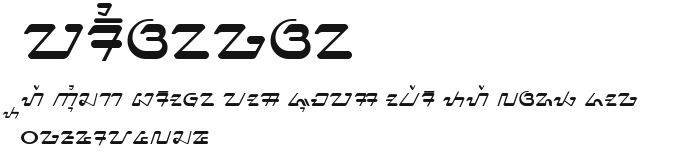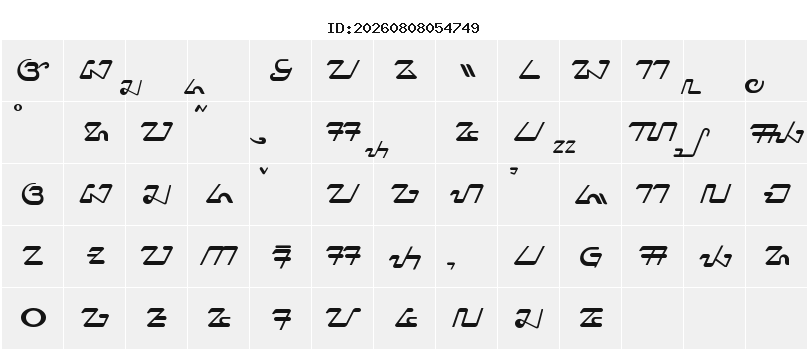
• Font Name: Priangan
• Designer: Indra Afriana
• Description: Aksara Sunda Baku nyaéta aksara Sunda kiwari nu diadaptasi ti aksara Sunda kuna. Teu sagemblengna sarua jeung aksara aslina. Aya sababaraha aksara nu dimodifikasi ti aksara aslina. Aya ogé aksara anu beda pisan jeung aksara aslina, contona aksara Nya, Ma, jeung I. Numutkeun filolog anu nyieun aksara ieu, tujuannya taya lian supaya barudak kiwari gampang ngalarapkeunna. Salian ti éta ogé keur ngagampangkeun merenahkeun disain fontna. Sakitu..
Priangan.ttf is a modern, elegant sans-serif font designed for ultimate readability and visual harmony. Perfect for branding, headlines, web design, and print materials.